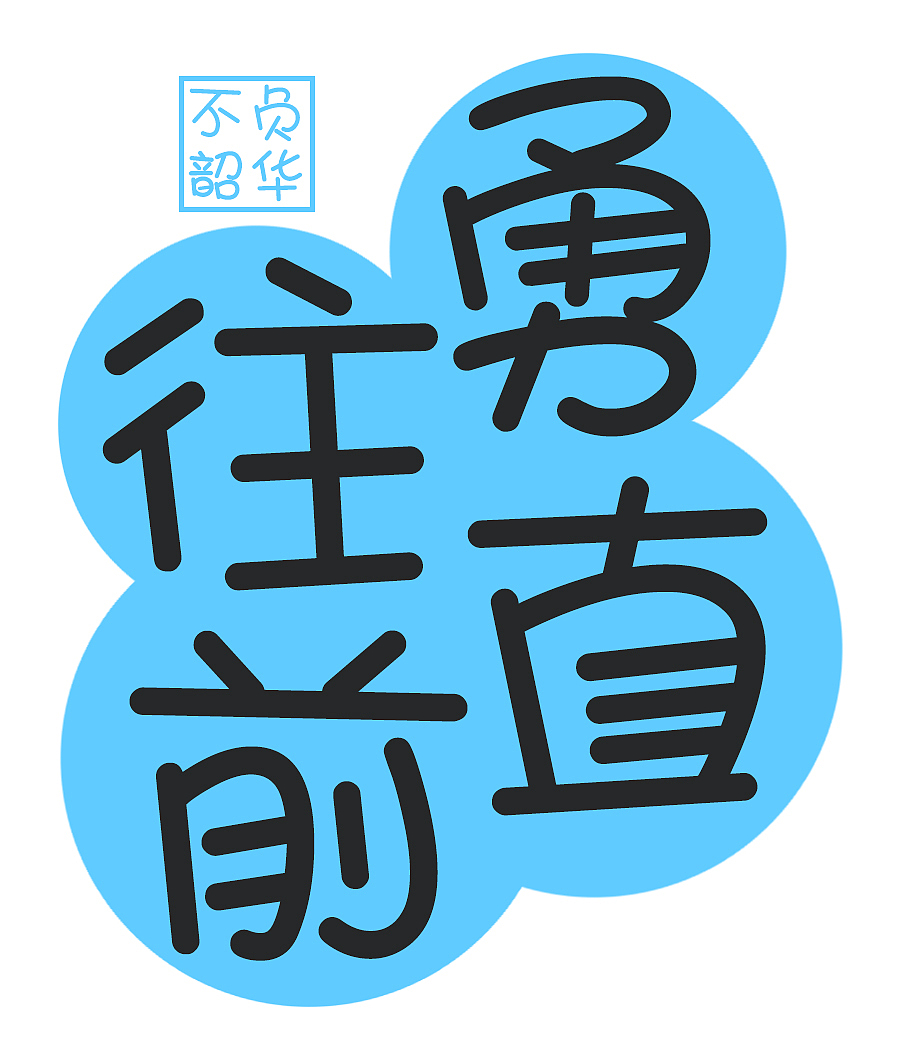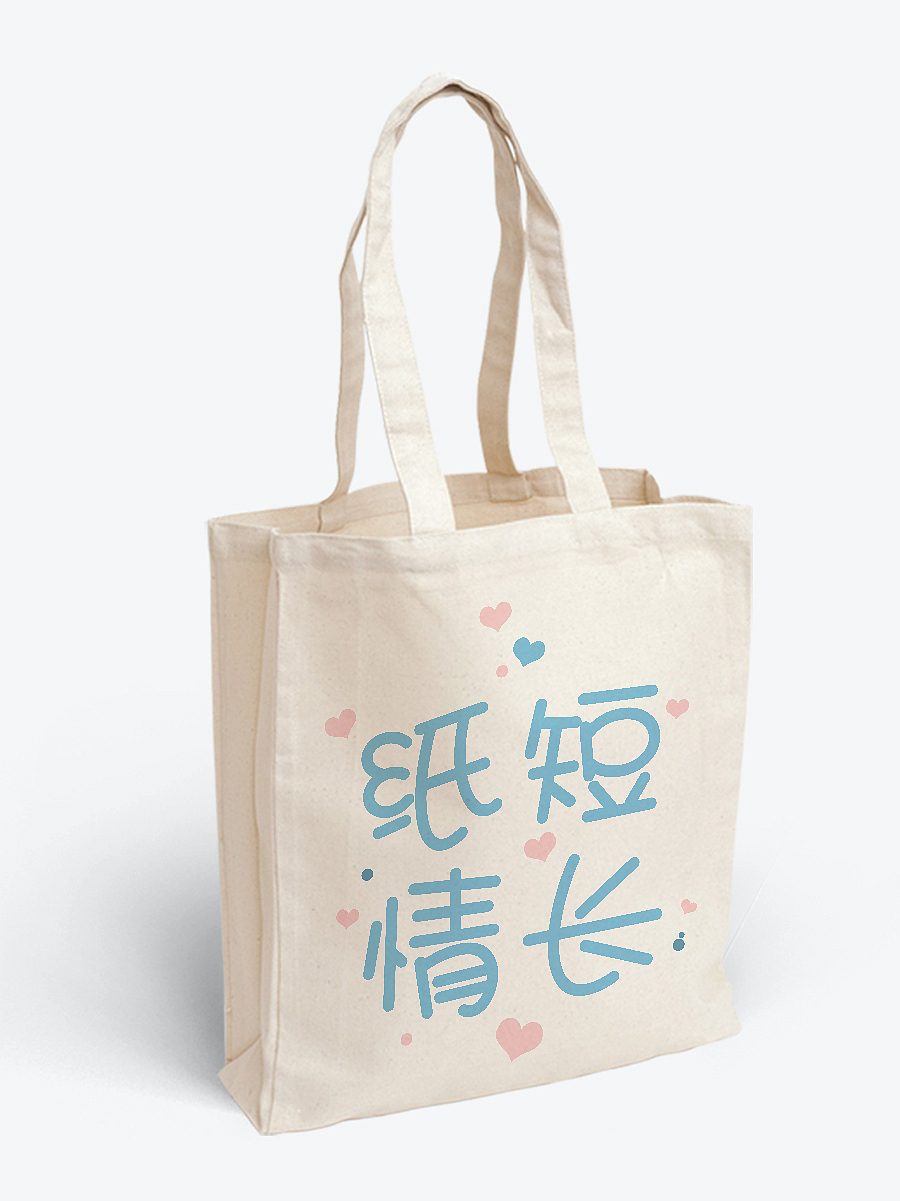
腾祥婀娜体 | 字体 | 海报 | 平面
腾祥婀娜体为POP手绘字体,是由设计师孔淼手绘完成每个字形的原稿,再由腾祥公司调整修改完成的美术体字库。整幅字风格统一、行文规整,字里行间充满童真稚趣,彰显活泼灵动的个性。笔画圆柔、舒缓随行、形同婀娜。
字体风格 | 艺术字体,手迹
适用范围 | 印刷用字、显示用字